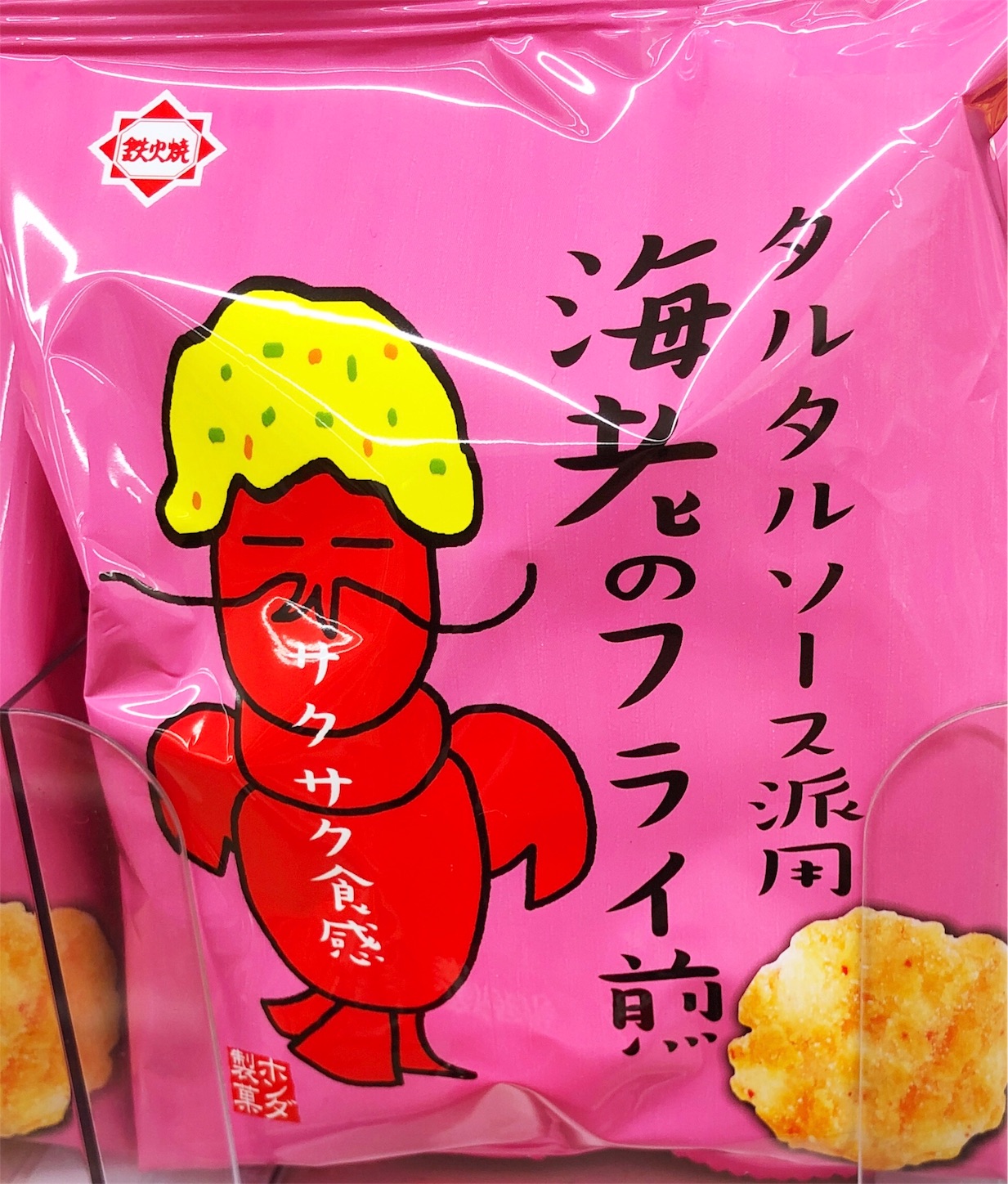
クラフトKANKAN
楷書体特有の重厚なストロークをベースにしながらも頭でっかちな重心や偏旁がアンバランスに見えるデザインなどがなんだかほっこりさせる、ゆるかわフォント。
クラフトKANKAN文字見本
クラフトKANKAKNが「鉄火焼 タルタルソース派用海老のフライ煎」に使用
ホンダ製菓の「鉄火焼 タルタルソース派用海老のフライ煎」のパッケージタイトルやテキストでクラフトKANKAKNが使用されている。